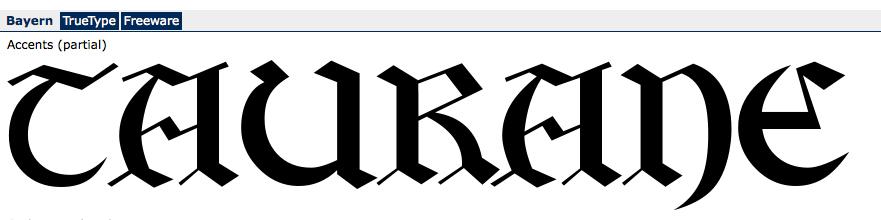
Keltische oder Altdeutsche Schrift gesucht
ich habe auf dafont ALLE keltischen und altdeutschen Schriften durchsucht, bin aber nicht fündig geworden.
Kennt hier jemand diese Schriftart?
Was in aller Welt hat das mit Bayern zu tun? :evil:
Aber immerhin hat Grobe Deutschmeister eben weder Bier noch Bayern im Namen. Ist ja was anderes, eine Schrift für typisch bayrisches zu nehmen, auch wenn sie ein "Preiß" gemacht hat, oder die Schrift nach Bayern zu benennen. Aber n Pülleken hätten sie schon mal rüber wachsen lassen können :-)